Eine kursiv Schriftart steht für Eleganz, Bewegung und Persönlichkeit.
Ob für Logos, Einladungen, Social Media oder kreative Headlines – kursive Schriften verleihen Texten einen handschriftlichen, emotionalen Charakter.
In diesem Artikel erfährst du, was eine kursive Schrift ausmacht, wann sie sinnvoll eingesetzt wird und welche modernen Script-Fonts sich besonders gut für professionelle Designs eignen.
Was ist eine kursive Schriftart?
Eine kursiv Schriftart zeichnet sich durch geneigte, fließende Buchstaben aus, die an Handschrift oder kalligrafische Schriftzüge erinnern.
Im Gegensatz zu klassischen Serif- oder Sans-Serif-Schriften wirkt Kursivschrift dynamischer und persönlicher.
Kursive Fonts werden häufig verwendet, um Emotionen zu transportieren, Akzente zu setzen oder Texte visuell hervorzuheben.
Wann du eine kursive Schriftart verwenden solltest
- 1. Für Logos & Branding: Ideal für feminine, kreative oder elegante Marken.
- 2. Für Social Media: Perfekt für Instagram-Posts, Bios und Story-Texte.
- 3. Für Einladungen & Karten: Verleiht Hochzeiten, Events und Grußkarten Stil.
- 4. Für Zitate & Highlights: Hebt einzelne Textpassagen wirkungsvoll hervor.
Eine kursiv Schriftart sollte gezielt eingesetzt werden – als Akzent oder Hauptschrift, je nach Designkonzept.
Die 7 besten kursiven Schriftarten für kreative Designs
Hier findest du sieben hochwertige kursive Schriftarten, die sich ideal für moderne, elegante und handschriftliche Designs eignen.
1. CS Gifted Script Font
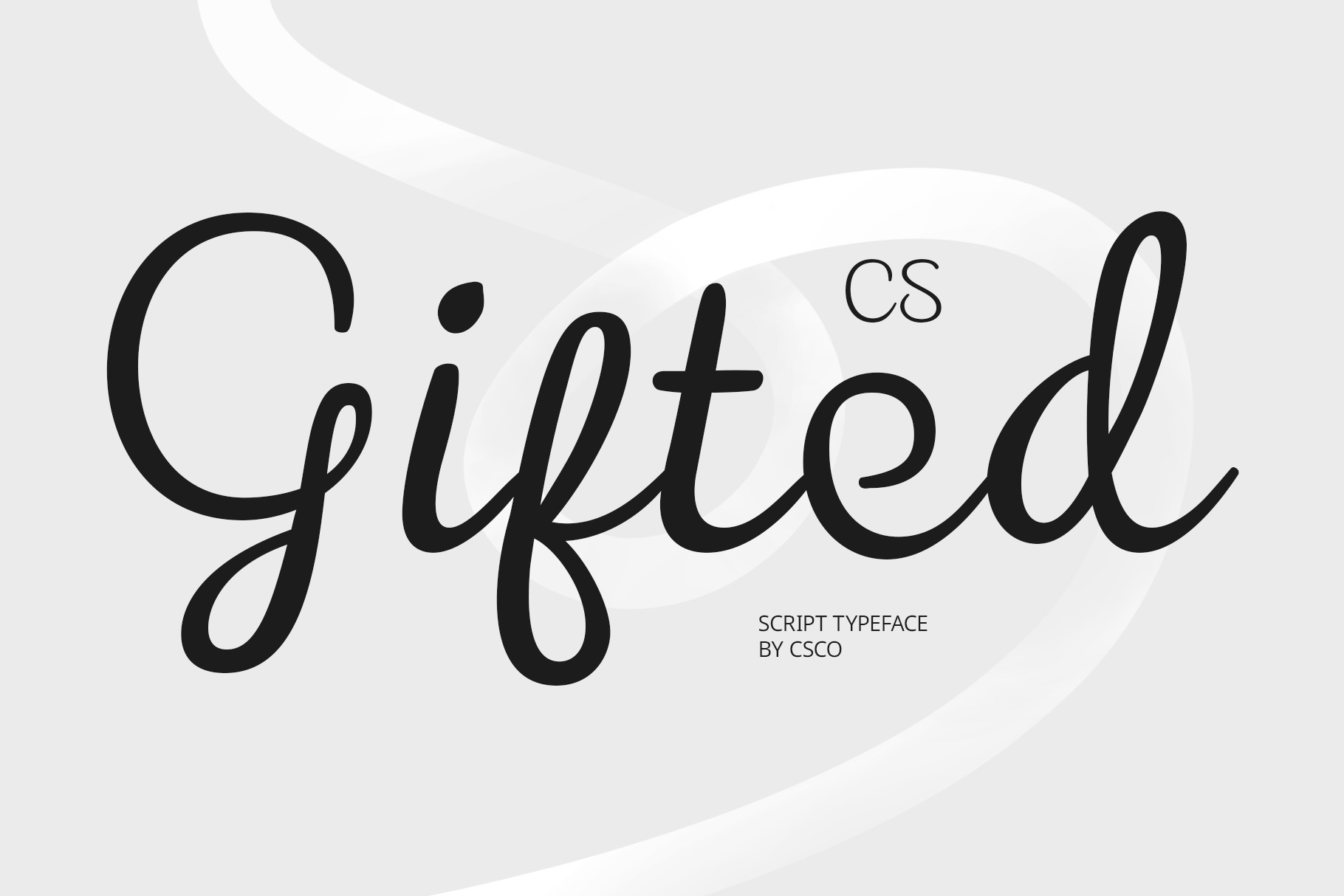
CS Gifted ist eine elegante Script-Schrift mit weichen Übergängen. Perfekt für Branding, Zitate und stilvolle Social-Media-Designs.
2. CS Glinka Script Font
Glinka überzeugt durch fließende, moderne Buchstabenformen. Ideal für feminine Designs, Logos und persönliche Projekte.
3. CS Gifted Drawn Font
Diese handgezeichnete Variante von Gifted wirkt lockerer und kreativer. Perfekt für Lifestyle-Designs und emotionale Botschaften.
4. CS Rafles Script Font
Rafles kombiniert klassische Kalligrafie mit moderner Lesbarkeit. Eine ausgezeichnete Wahl für elegante Headlines und Logos.
5. CS Mercy Script Font
Mercy ist weich, harmonisch und sehr gut lesbar. Ideal für Hochzeitsdesigns, Einladungen und stilvolle Printprodukte.
6. CS Melanie Etchy Font
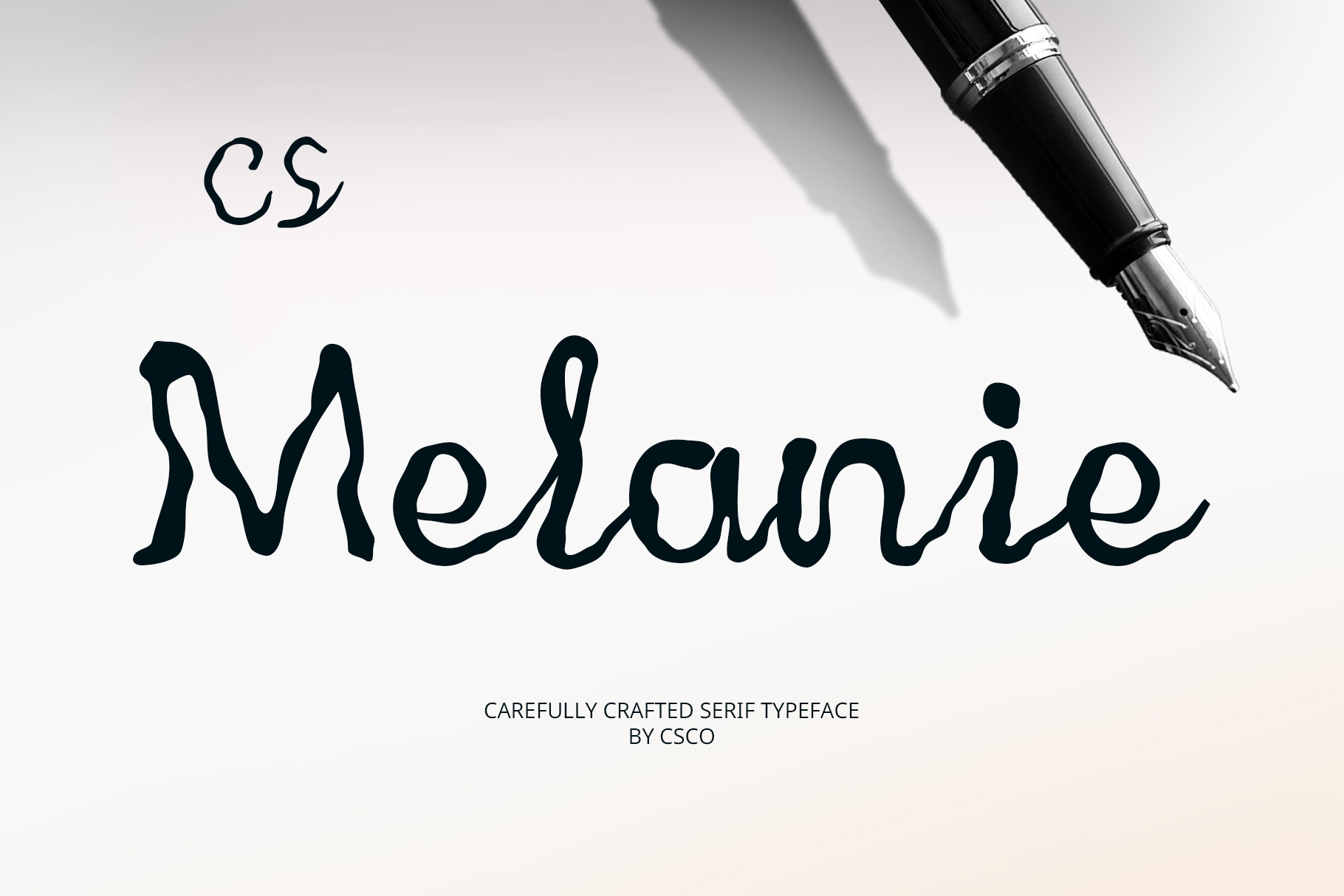
Melanie Etchy bringt einen künstlerischen, leicht rauen Look mit. Perfekt für kreative Projekte mit handgemachtem Charakter.
7. CS Hailey Script Font
Hailey ist modern, feminin und elegant. Besonders beliebt für Instagram, Branding und stilvolle Webdesigns.
Design-Tipps für kursive Schriftarten
- 1. Weniger ist mehr: Nutze kursive Schriften gezielt als Highlight.
- 2. Kombiniere mit Sans Serif: Sorgt für Balance und gute Lesbarkeit.
- 3. Achte auf Abstände: Script-Fonts brauchen oft mehr Luft.
- 4. Teste die Lesbarkeit: Besonders bei kleinen Schriftgrößen.
Fazit: Kursiv Schriftart für elegante Typografie
Eine kursiv Schriftart verleiht deinem Design Persönlichkeit, Eleganz und emotionale Tiefe.
Ob modern, handschriftlich oder kalligrafisch – die richtige Script-Schrift kann dein Projekt deutlich aufwerten.
Mit den vorgestellten Fonts findest du garantiert eine kursive Schrift, die perfekt zu deinem Stil passt.